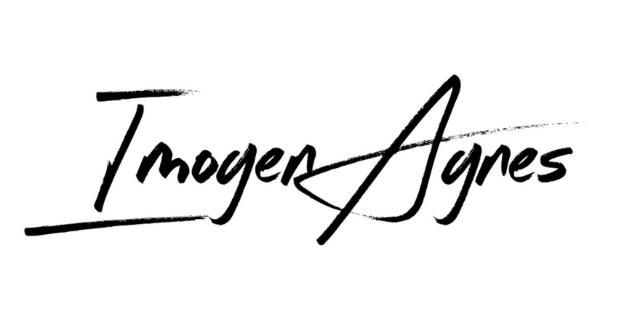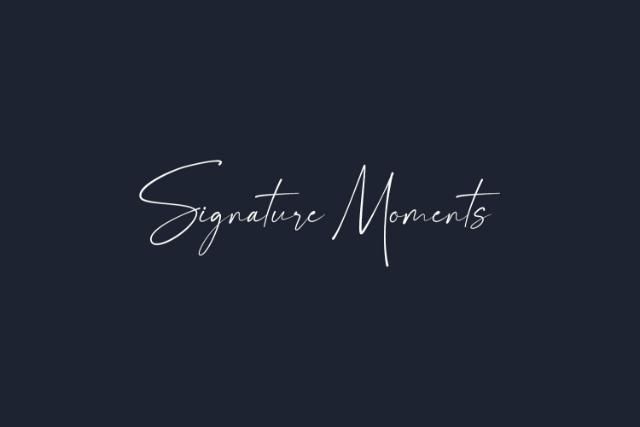
Trong kỷ nguyên số, một chữ ký cá nhân hay logo thương hiệu không chỉ là dấu hiệu nhận biết mà còn là “tuyên ngôn” về đẳng cấp và sự chuyên nghiệp. Bài viết này sẽ cung cấp cho bạn một cái nhìn chuyên sâu nhất, đồng thời tổng hợp hơn 10+ font chữ ký đẹp nhất hiện nay (đã được Việt hóa chuẩn). Chỉ với vài thao tác đơn giản, bạn hoàn toàn có thể ứng dụng ngay vào thiết kế logo, name card hay tạo chữ ký email một cách vô cùng dễ dàng và ấn tượng.
Font chữ ký đẹp là gì?
Font chữ ký là kiểu chữ được tạo ra dựa trên nét viết tay tự nhiên giúp thiết kế trở nên mềm mại, chân thực và mang dấu ấn cá nhân hơn. Loại font này thường được dùng để làm nổi bật logo, thiệp mời, poster, chữ ký điện tử hoặc các ấn phẩm cần sự tinh tế và khác biệt.
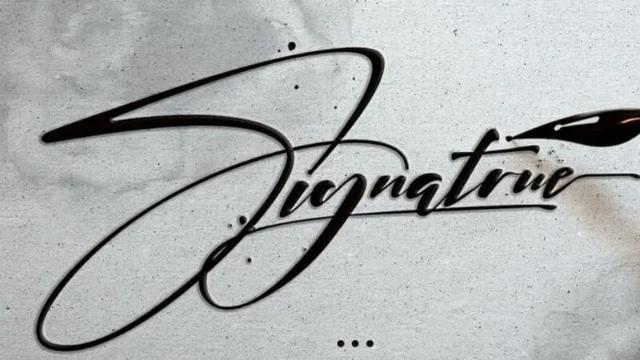
Đặc điểm nổi bật của font chữ ký
- Mang phong cách viết tay tự nhiên: Font chữ ký được thiết kế mô phỏng nét chữ viết tay thật, với các đường nét mềm mại, uyển chuyển và không quá khuôn mẫu. Nhờ đó, kiểu chữ này tạo cảm giác gần gũi, cá nhân và tự nhiên hơn trong thiết kế.
- Đa dạng phong cách sử dụng: Font chữ ký có nhiều kiểu dáng khác nhau, từ nét mảnh nhẹ nhàng, bay bổng đến nét đậm mạnh, cá tính. Người dùng có thể lựa chọn theo nhiều phong cách như thanh lịch, nghệ thuật, thời trang, hiện đại hoặc sang trọng.
- Có tính thẩm mỹ cao: Font chữ ký giúp tổng thể thiết kế trở nên nổi bật, tinh tế và giàu cảm xúc hơn. Đây là lựa chọn phù hợp cho thiết kế thương hiệu, thiệp cưới, sản phẩm handmade, logo cá nhân hoặc các ấn phẩm cần tạo dấu ấn riêng.
Tổng hợp các loại Font chữ ký đẹp phổ biến nhất hiện nay
Việc lựa chọn đúng font chữ ký không chỉ giúp tác phẩm thiết kế trở nên hút mắt mà còn là cách định vị thương hiệu vô cùng sắc bén. Dưới đây là bộ sưu tập các font chữ ký xuất sắc nhất, được chắt lọc từ những kho tài nguyên uy tín hàng đầu của cộng đồng Designer Việt Nam. Các nhóm font được phân loại rõ ràng theo từng phong cách để bạn dễ dàng đối chiếu và ứng dụng ngay vào dự án của mình.
Nhóm Font chữ ký các nhân đẹp cho thiết kế Logo
Nếu bạn đang tìm kiếm một “linh hồn” cho dự án thiết kế nhận diện thương hiệu cá nhân (Personal Branding), 3 cái tên dưới đây chính là những tượng đài không thể xô đổ:
- Font Autography: Được ví như chữ ký “quốc dân”, Autography sở hữu những nét chữ mềm mại, bay bổng cùng độ nghiêng tự nhiên vô cùng chân thực. Font chữ này đánh lừa thị giác người xem một cách hoàn hảo, khiến họ tin rằng đây là nét bút ký tay thực sự. Autography cực kỳ phù hợp để làm watermark bảo vệ bản quyền đóng góc các bức tranh nghệ thuật (như tranh sơn dầu) hoặc logo cho các nhiếp ảnh gia.
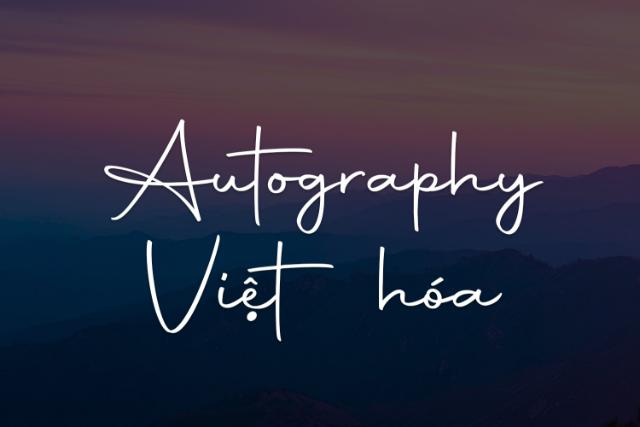
- Font Creattion: Khác với sự bay bổng của Autography, Creattion mang hơi thở hiện đại và cấu trúc nét chặt chẽ hơn. Điểm ăn tiền của font này là các nét thanh đậm được phân chia vô cùng rõ ràng mang lại cảm giác dứt khoát, quyền lực nhưng không kém phần thanh lịch. Rất phù hợp để thiết kế logo cho các doanh nghiệp, gallery nghệ thuật cao cấp.
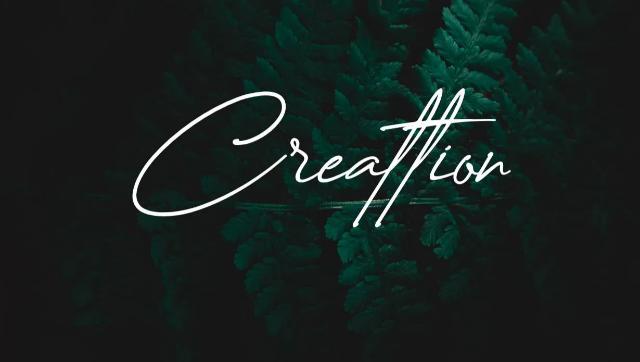
- Font The Historia: Đây là sự lựa chọn số một cho những tâm hồn yêu thích nét đẹp hoài niệm. The Historia mang đậm phong cách vintage, nghệ thuật với những đường vuốt đuôi (swash) đầy ngẫu hứng. Nếu bạn đang thiết kế ấn phẩm cho các không gian trưng bày truyền thống, hay các bộ sưu tập tranh sơn mài đậm chất văn hóa, The Historia sẽ truyền tải trọn vẹn tinh thần nghệ thuật đó.
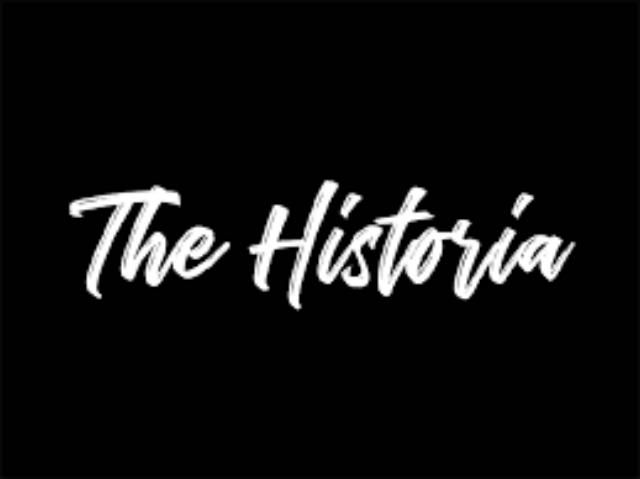
Nhóm Font chữ ký Việt Hóa đẹp hoàn hảo, không lỗi dấu
“Lỗi dấu tiếng Việt” là cơn ác mộng lớn nhất của bất kỳ Designer nào. Để đảm bảo tính chuyên nghiệp tuyệt đối, bạn hãy lưu ngay các bộ font đã được Việt hóa chuẩn chỉnh dưới đây:
- Font SVN-Astrud: Nhắc đến font chữ ký Việt hóa không thể bỏ qua bộ SVN, và Astrud là một “viên ngọc sáng” trong số đó. Với nét chữ thanh mảnh, độ lơi vừa phải, SVN-Astrud không bao giờ bị vỡ nét khi gõ các dấu phức tạp. Đây là chân ái cho các thiết kế thiệp cưới, thư mời sự kiện hoặc branding cho các thương hiệu thời trang sang trọng.
- Bộ Font Iciel (Các dòng Script): Cộng đồng thiết kế Việt Nam luôn đánh giá rất cao độ hoàn thiện của kho font Iciel. Các dòng Script của Iciel được tối ưu hóa phần kerning (khoảng cách chữ), giúp các nét nối liền mạch hoàn hảo 100% khi gõ tiếng Việt, tạo nên dòng chảy thị giác trơn tru, không hề có cảm giác gượng gạo.
- Bộ Font UTM (Dòng Script/Handwriting): Nếu bạn cần sự phá cách, UTM chính là bộ “font quốc dân” đáp ứng mọi nhu cầu. Các dòng chữ ký tay của UTM thường có độ xước nhẹ, nét bút mạnh mẽ, dứt khoát, rất được lòng nam giới, các photographer thể thao hoặc các thương hiệu có cá tính mạnh.
- Một số Font viết tay mặc định đã việt hóa nổi bật khác:
- SVN-Nexa Script: Sự kết hợp hoàn hảo giữa nét viết tay và tỷ lệ hình học chuẩn, rất hiện đại và dễ đọc.
- HL Brush: Phông chữ mô phỏng nét cọ vẽ (brush) ấn tượng, phù hợp cho các thiết kế poster nghệ thuật, bảng hiệu cần điểm nhấn mạnh.
- Caster (Bản Việt hóa): Nét chữ tròn trịa, thân thiện và mang lại cảm giác năng lượng tích cực.
Một font chữ ký đẹp không chỉ giải quyết bài toán thẩm mỹ mà còn là khoản đầu tư thông minh để gia tăng giá trị nhận diện, xây dựng sự tin tưởng và khẳng định vị thế của cá nhân lẫn doanh nghiệp trong tâm trí khách hàng.